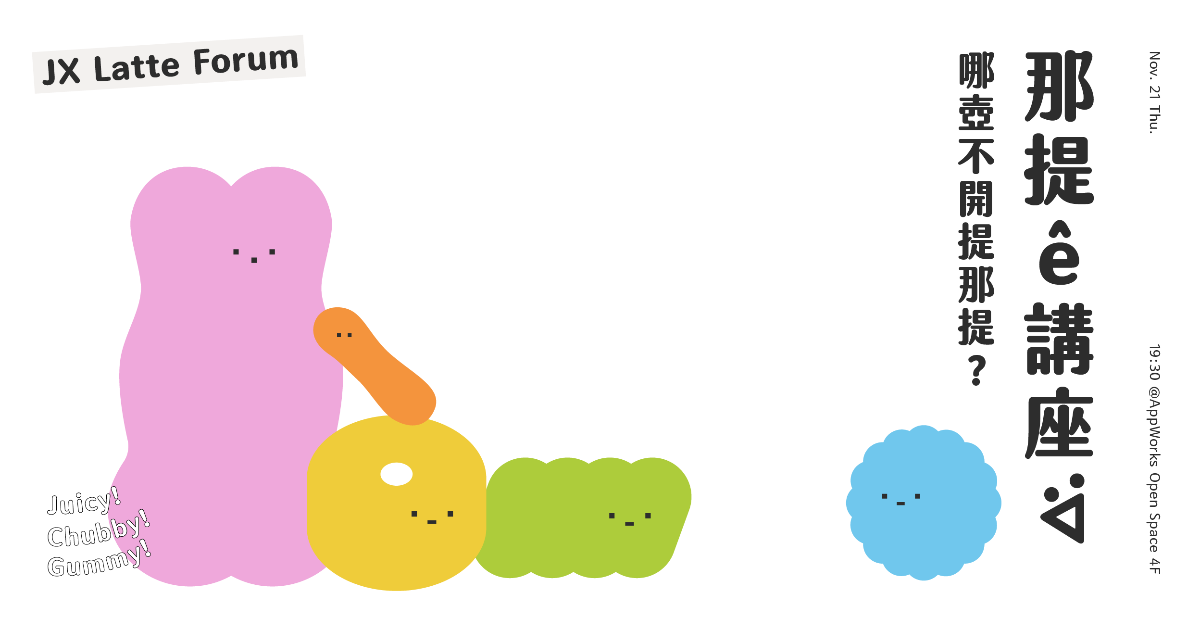
2017 年 4 月 1 日,我們在「字戀」發表了「金萱那提」⋯⋯原來把金萱變成圓的,就是金萱那提了呀!本來只是想在愚人節刷一下存在感。但兩年之後,這個愚人節笑話竟然成為真正的字型家族(如同寶可夢 GO?)。在這場講座中,我們就是要與您分享一套字型從抽象概念成為真實的奇幻旅程。
justfont 字型設計師們與字型總監霞姐將會分享金萱那提的:
- 漢字設計:如何設計一個圓圓的字體而不失平衡與質感?
- 歐文與符號設計:ABCD、標點注音的設計,如何與漢字風格保持一致?
- 台羅拼音設計:複雜的聲調記號是怎麼一回事,要怎麼調整?
那提正式上線之後,字型設計師們終於有時間好好談談他們這段時間的磨難與心得,邀請已經收藏金萱那提的您來聽他們分享。